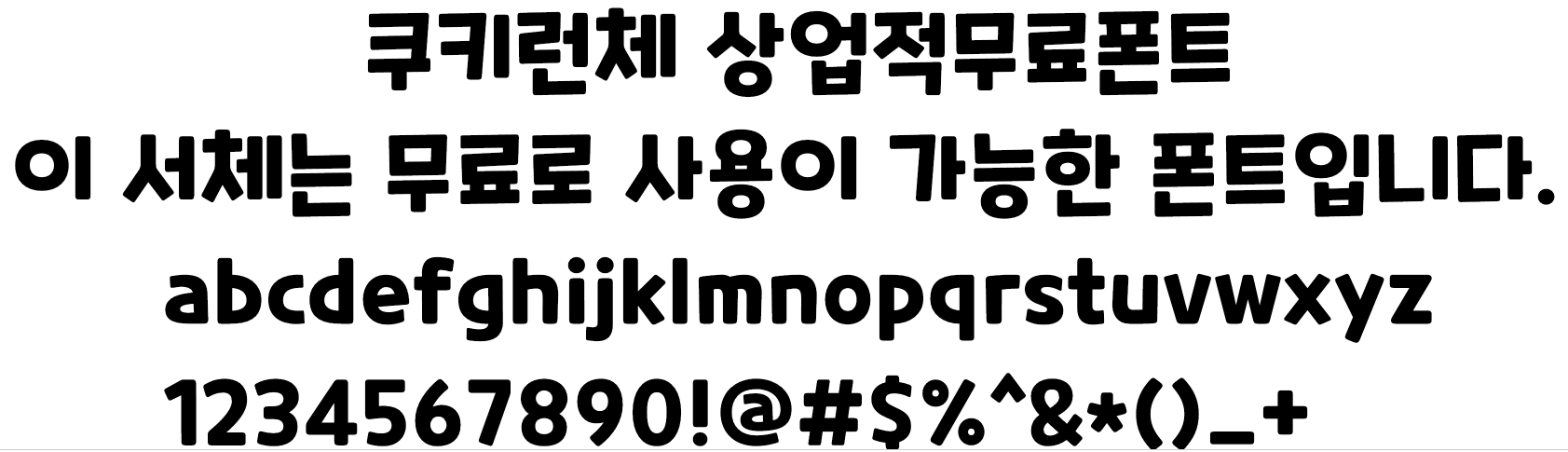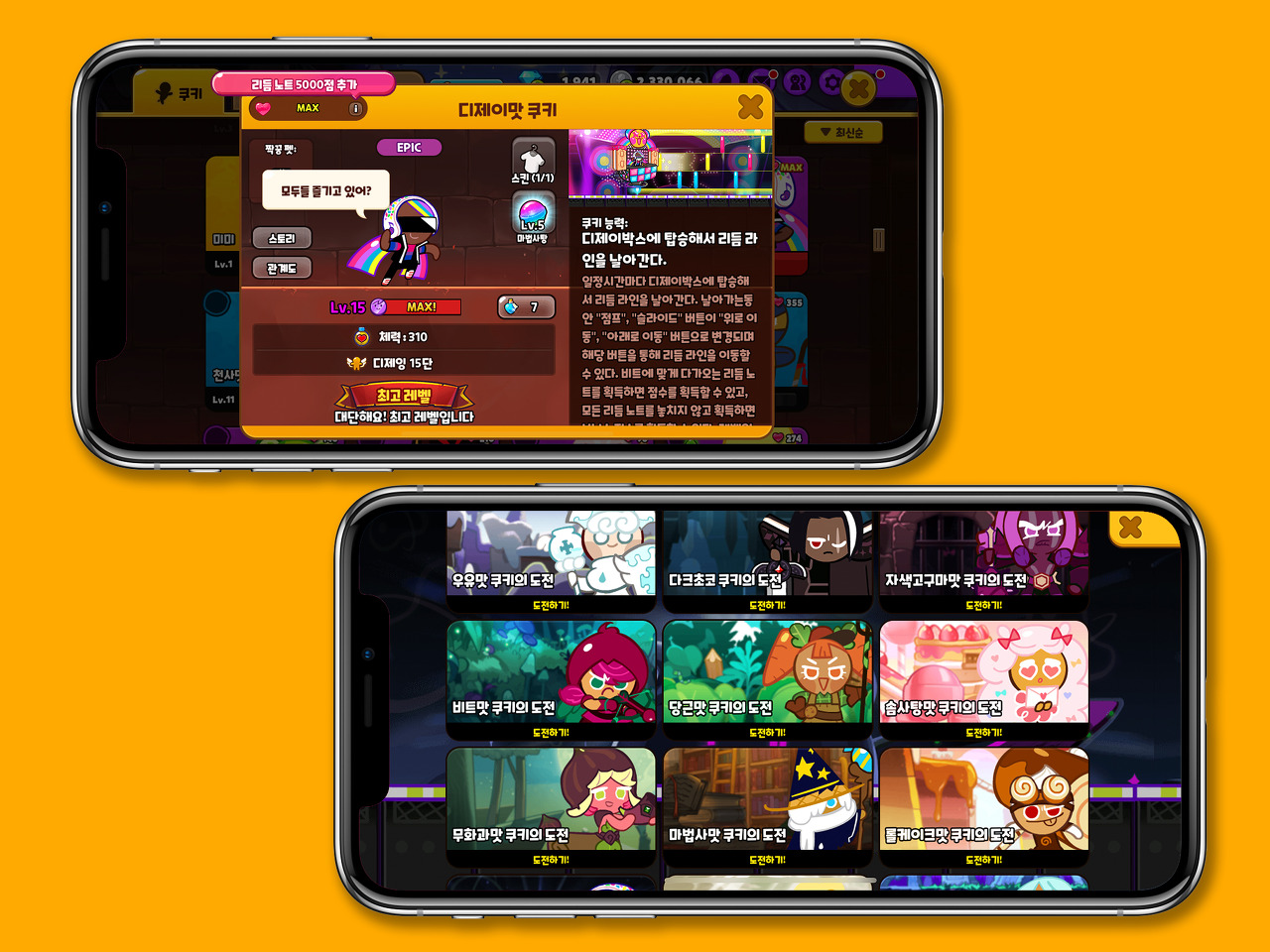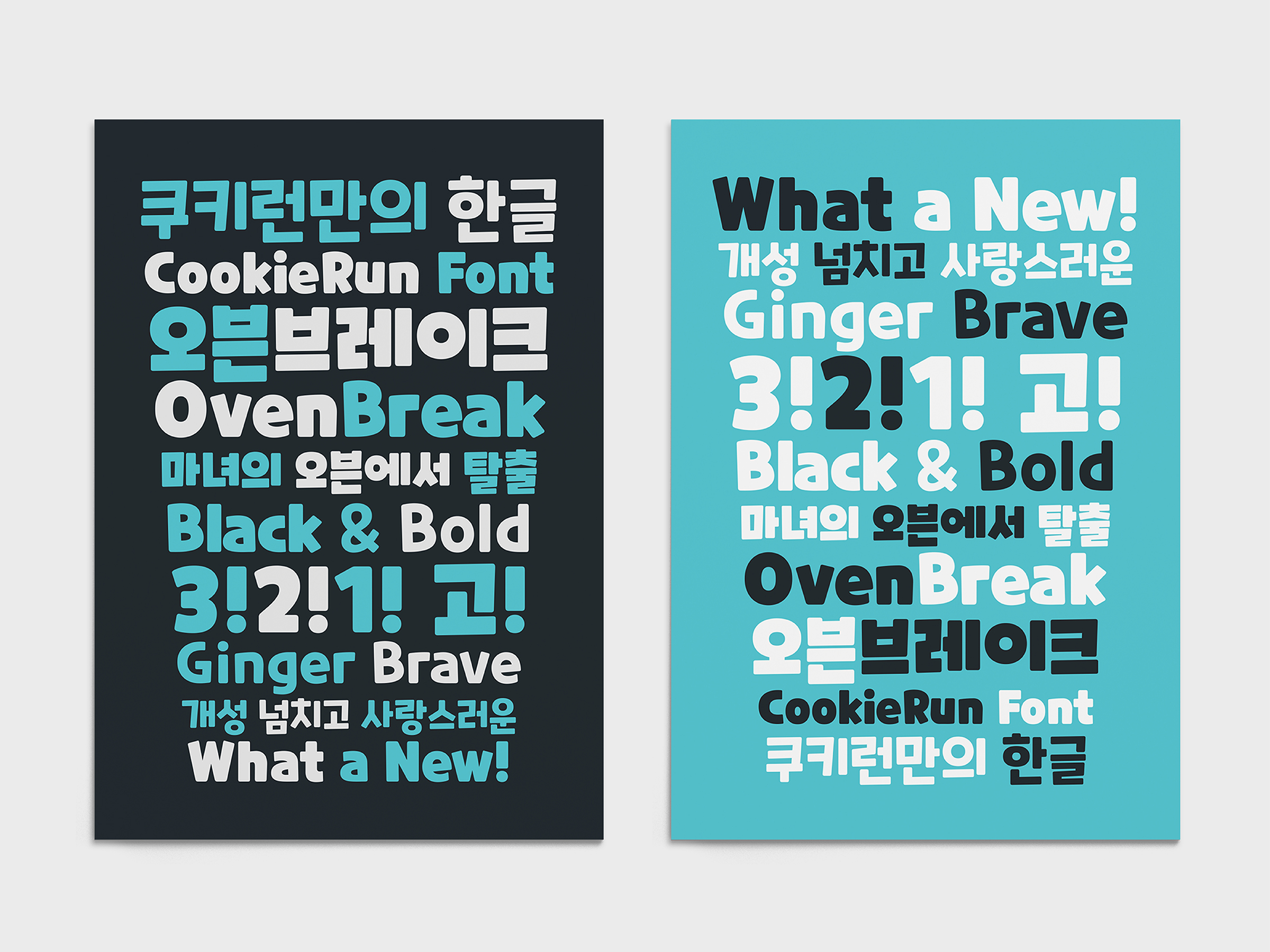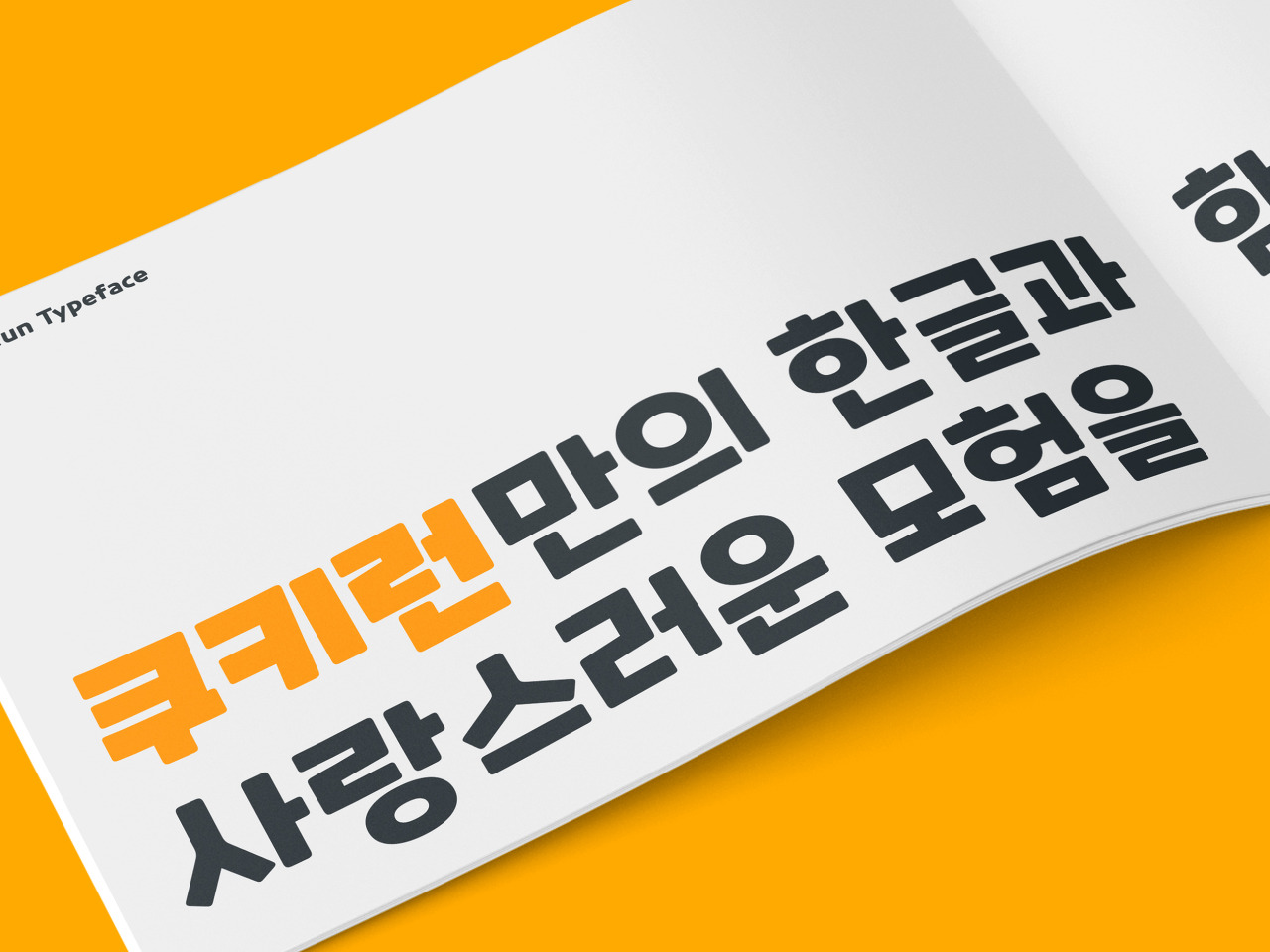
상업적 무료폰트 - 쿠키런 폰트 다운로드
"상업적무료폰트 쿠키런체"
쿠키런체
데브시스터에서 만든 쿠키런체는 쿠키런의 아이피를 활용하면서 게임에 잘 어울리는 폰트를 개발하여 여러분들이 무료로 사용할 수 있게 배포중입니다. Regular, Bold, Black 3가지를 사용할 수 있습니다. 부드럽게 손으로 꾹꾹눌러쓴것과 같은 느낌의 폰트로 눈에 잘띄면서도 반듯한 느낌을 낼때 제격인 폰트입니다.